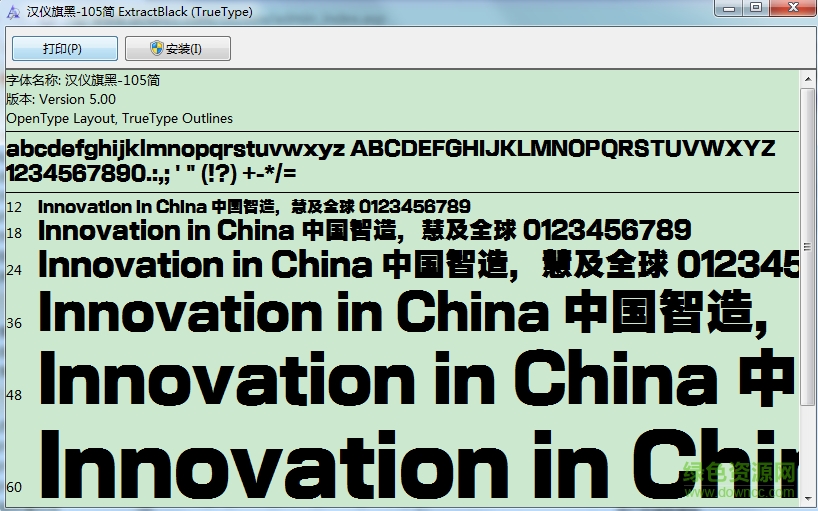
hyqihei hes字體也就是漢儀旗黑-85S簡字體,這款字體筆畫粗壯,結(jié)構(gòu)簡潔大方,整體效果非常出色,非常適用于排版印刷,廣告設(shè)計(jì)等領(lǐng)域,喜歡這款字體的朋友歡迎來綠色資源網(wǎng)免費(fèi)下載使用。
hyqihei hes字體是一款漢儀字體庫中的常用的字體,字型外觀整齊,功能性較強(qiáng),整體效果非常出色,有喜歡的朋友就來綠色資源網(wǎng)下載使用吧!